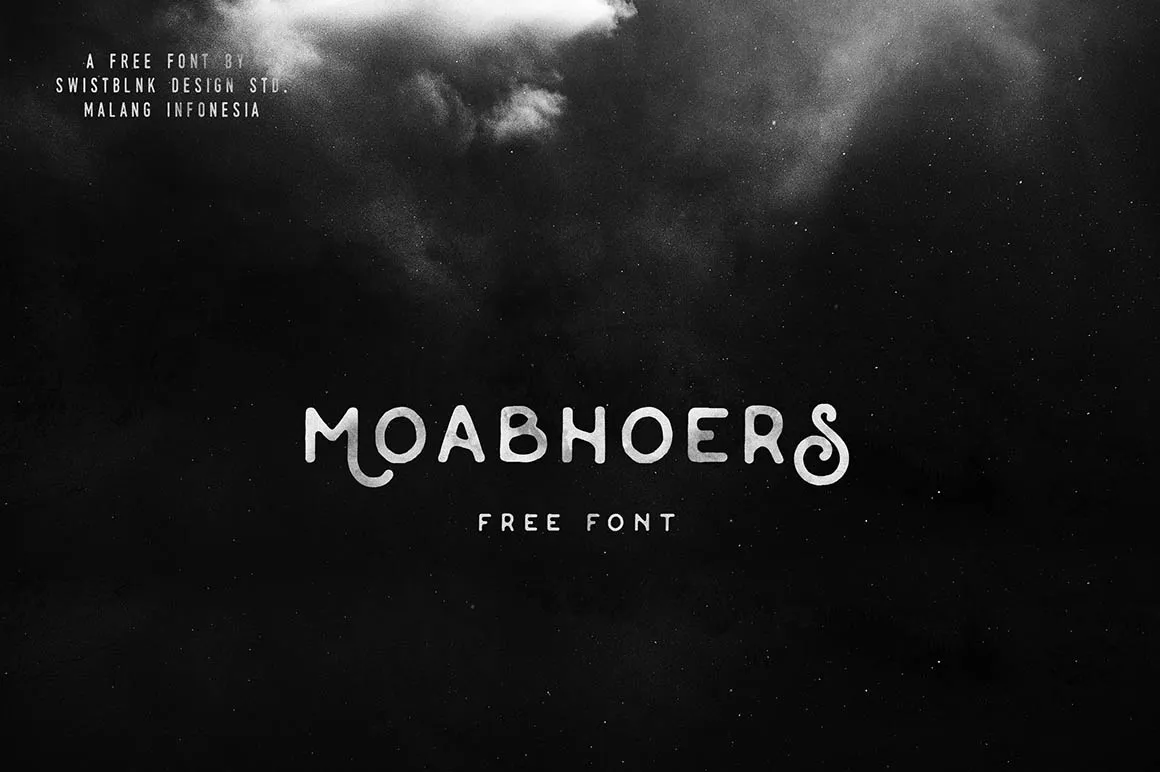
Moabhoers Font – Fonte Grátis
Moabhoers Font
A Moabhoers Font é uma elegante escolha para quem busca um estilo vintage retro na sua tipografia. Criada pelo designer Hamilton, essa fonte blackletter traz uma vibe vintage que remonta ao gótico moderno e grunge dos anos 90. Com uma composição em letras maiúsculas única e incrivelmente vintage, esta fonte não só é ideal para uso no design editorial, mas também em aplicativos de mídias sociais ou até mesmo rascunhos pessoais. O que realmente torna essa fonte especial são seus caracteres especiais adicionados ao design. Ela carrega um toque único e distinto que torna qualquer projeto mais interessante e profissional, sem perder a essência vintage do seu estilo. A Moabhoers Font é uma versão customizada de Agga Swist’blnk e oferece um visual inconfundível para quem está buscando uma fonte blackletter no estilo retro/vintage para seus projetos digitais. Descarregue e use a Moabhoers Font com prazer, que ela certamente dará o toque final perfeito ao seu próximo design.